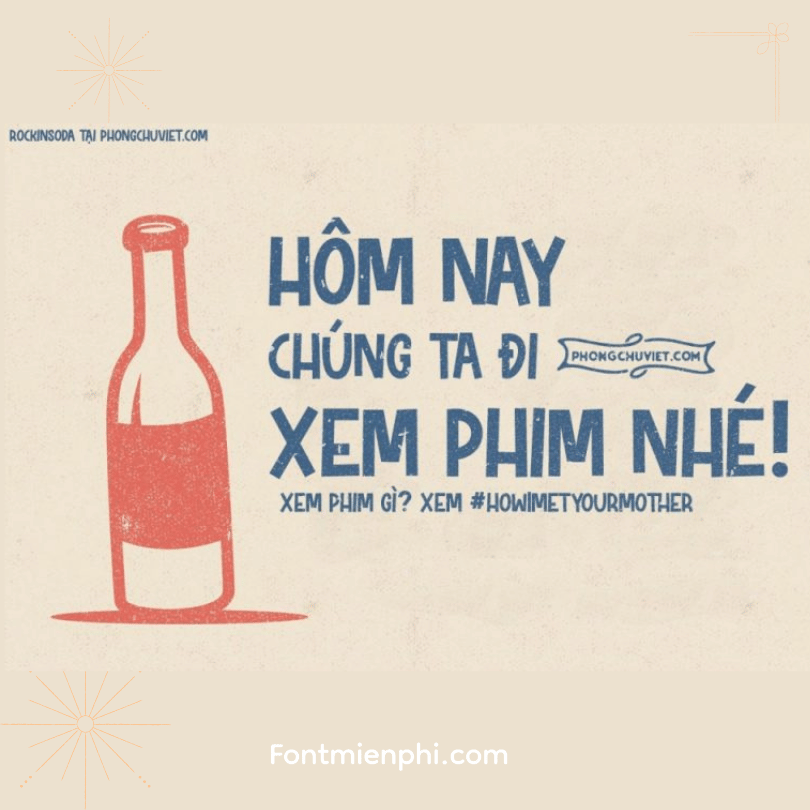
Việt hóa font FS Rockinsoda
Cách Việt hóa font FS Rockinsoda Chuẩn Designer
FS Rockinsoda là font chữ display cá tính với nét đứt độc đáo, thường dùng cho poster âm nhạc, thiết kế streetwear. Đây là cách việt hóa hiệu quả:
1. Kiểm tra bản gốc
• Test nhanh: Gõ “Thiết kế Rock” trong AI/PS
• ✓ Hiển thị đủ dấu: Dùng được ngay
• ✗ Mất dấu: Cần chỉnh sửa
2. Giải pháp việt hóa
Option 1: Dùng bản đã chỉnh sửa
Option 2: Tự chỉnh sửa
• Cần thêm:
• Bộ ký tự Việt (ă, â, đ, ê, ơ…)
• Cân chỉnh dấu thanh cho các nét đứt
• Fix lỗi kerning với chữ hoa có dấu
Option 3: Font thay thế
3. Lưu ý quan trọng